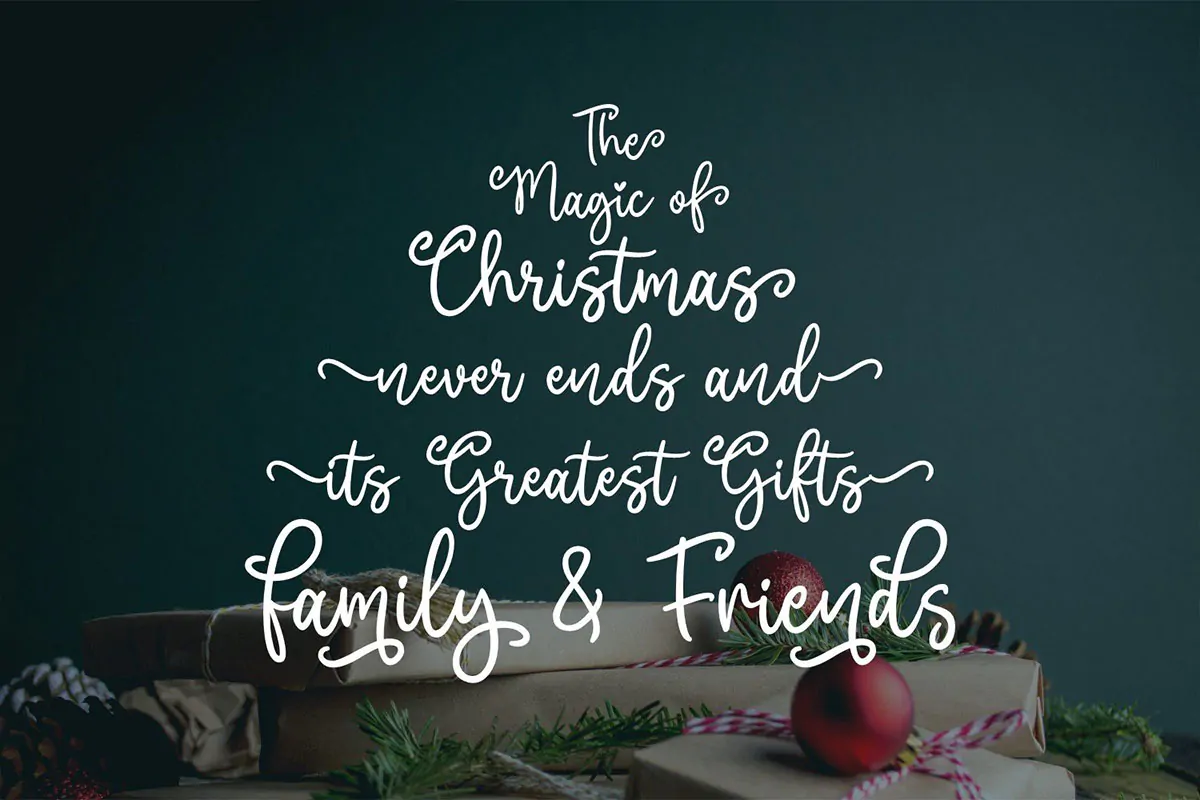
فونت دستنویس کریسمس Jolly Holly
فونت دستنویس کریسمس
فونت دستنویس کریسمس Jolly Holly یک اسکریپت فونت فوق العاده زیبای انگلیسی است که میتوانید در طرحهای گرافیکی مختلف به خصوص طراحی انواع کارت از آن استفاده کنید.